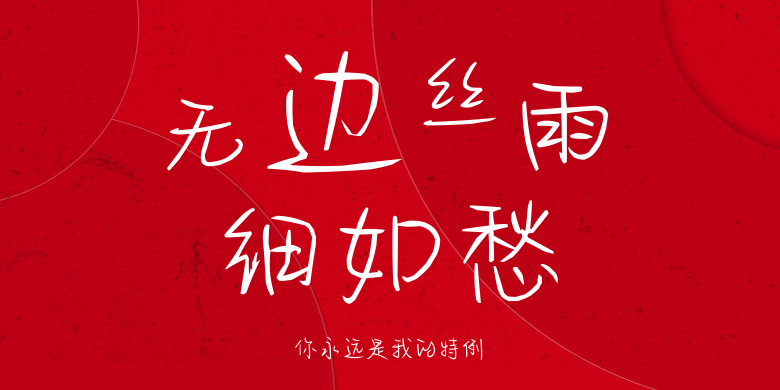
你永远是我的特例
你永远是我的特例,这款字体结构工整、笔画清晰,兼顾美观与易读性,适用于标题、正文、海报、包装、LOGO 等多种场景。字形优雅稳定,风格百搭耐看,适配日常排版与创意设计,让文字呈现更舒适、更具质感。你永远是我的特例一笔一画,皆是细节,以均衡的比例、流畅的线条打造舒适视觉体验,字形端正大气,风格简约现代。无论是商业设计、品牌宣传还是日常排版,都能轻松驾驭,让文字更有格调与力量。你永远是我的特例字体下载。